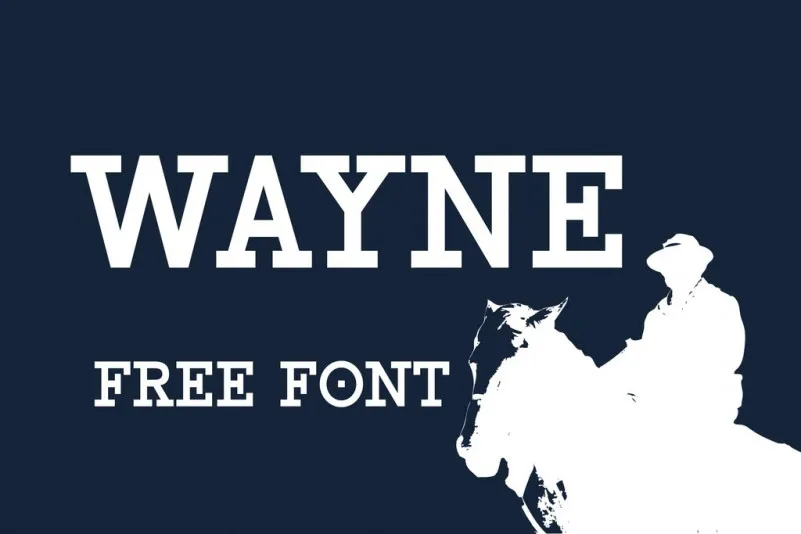
Esta fonte Wayne Font é perfeitamente projetada para aumentar a legibilidade ao oferecer um belo tipo slab serif. Bravely Lion Fonts criou essa font que pode ser utilizada para uma ampla variedade de necessidades e projetos, seja para redes sociais ou identidade visual, desenho de moda ou design impresso. Ela é perfeita para usar em cartazes de marca social, designs de roupas, citações impressas, embalagens e até mesmo como overlay de texto sofisticado sobre qualquer imagem de fundo. Seja qual seja o seu projeto, Wayne Font está aqui para ajudar a torná-lo único e atraente.